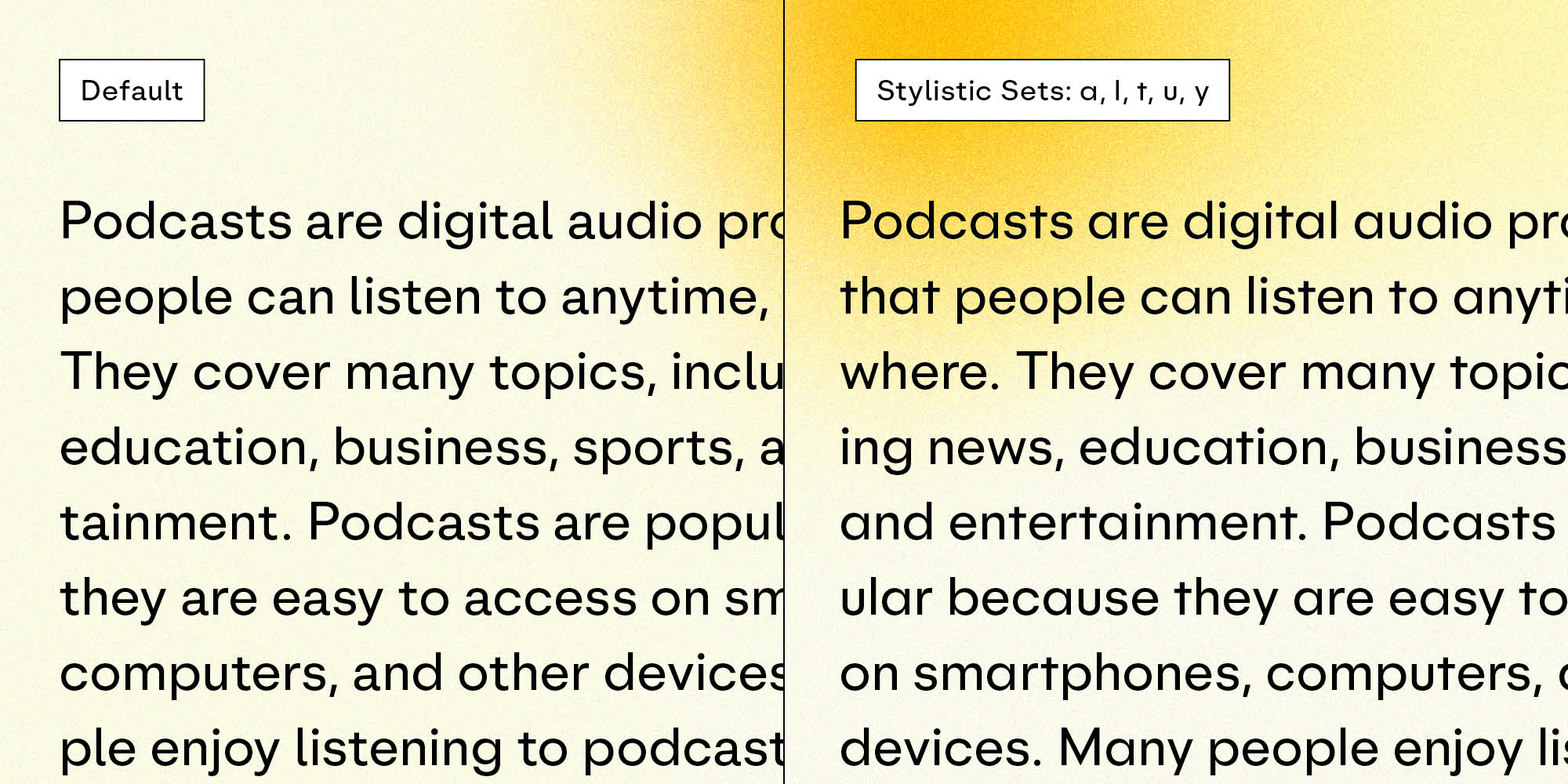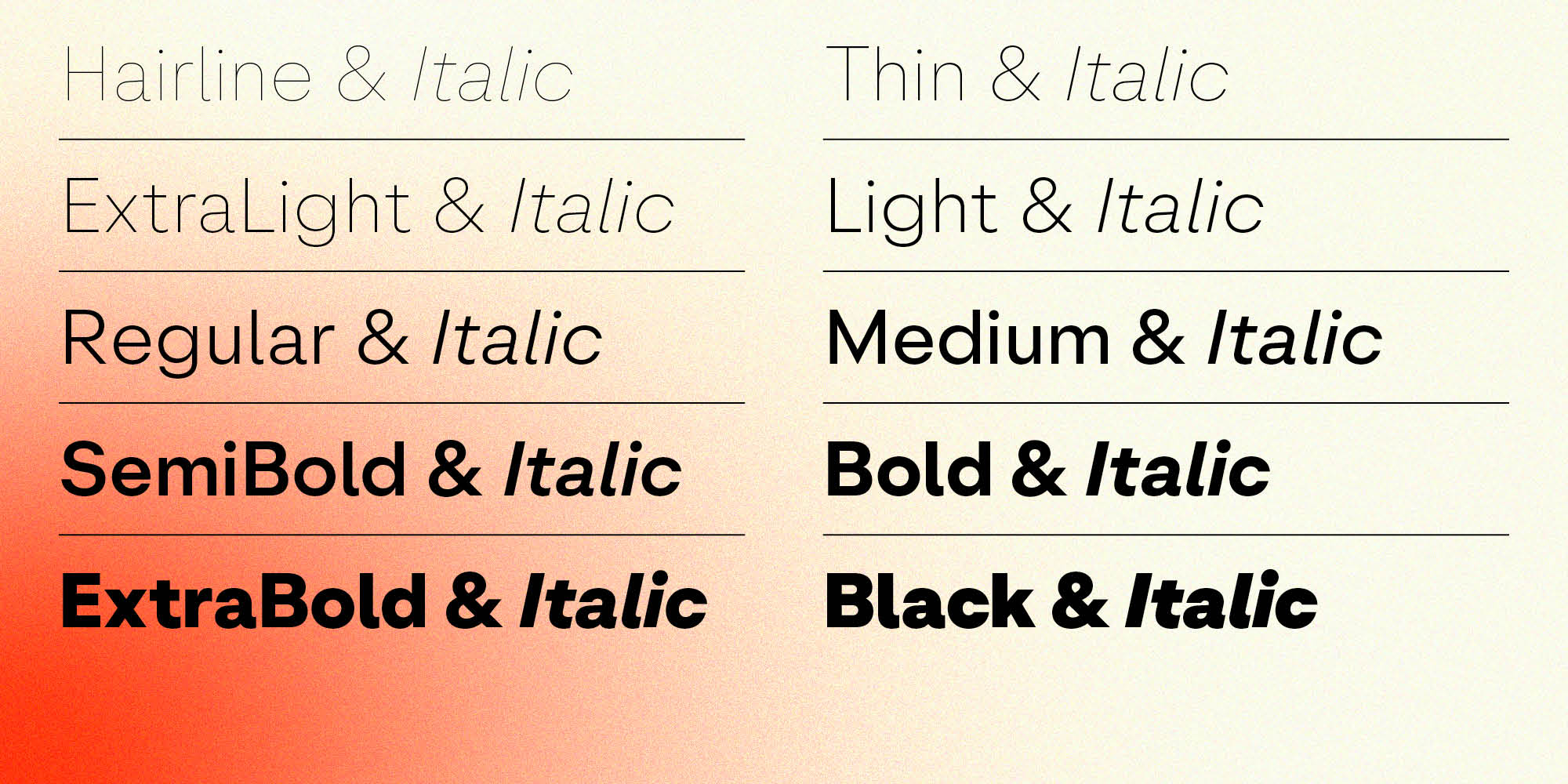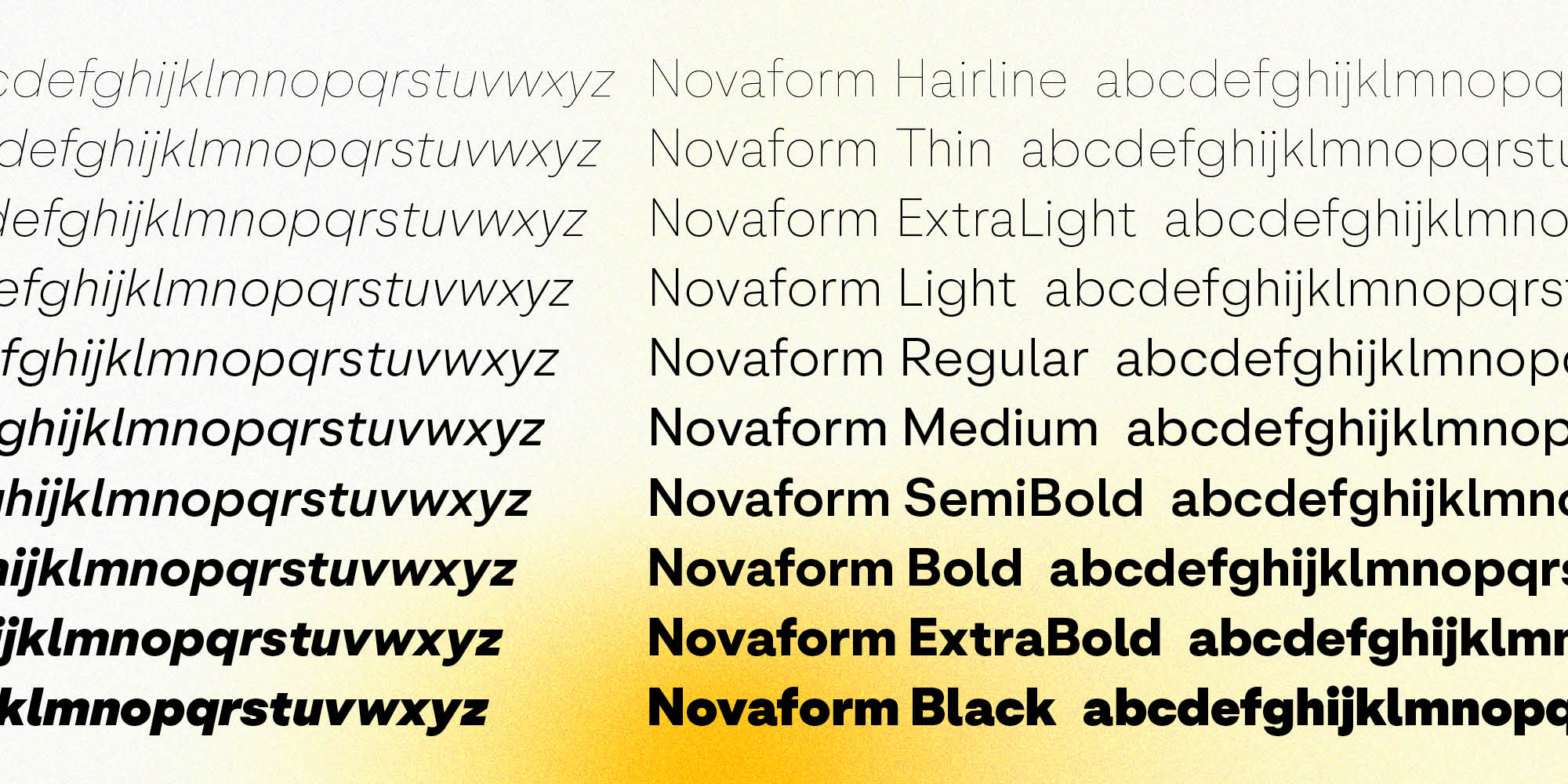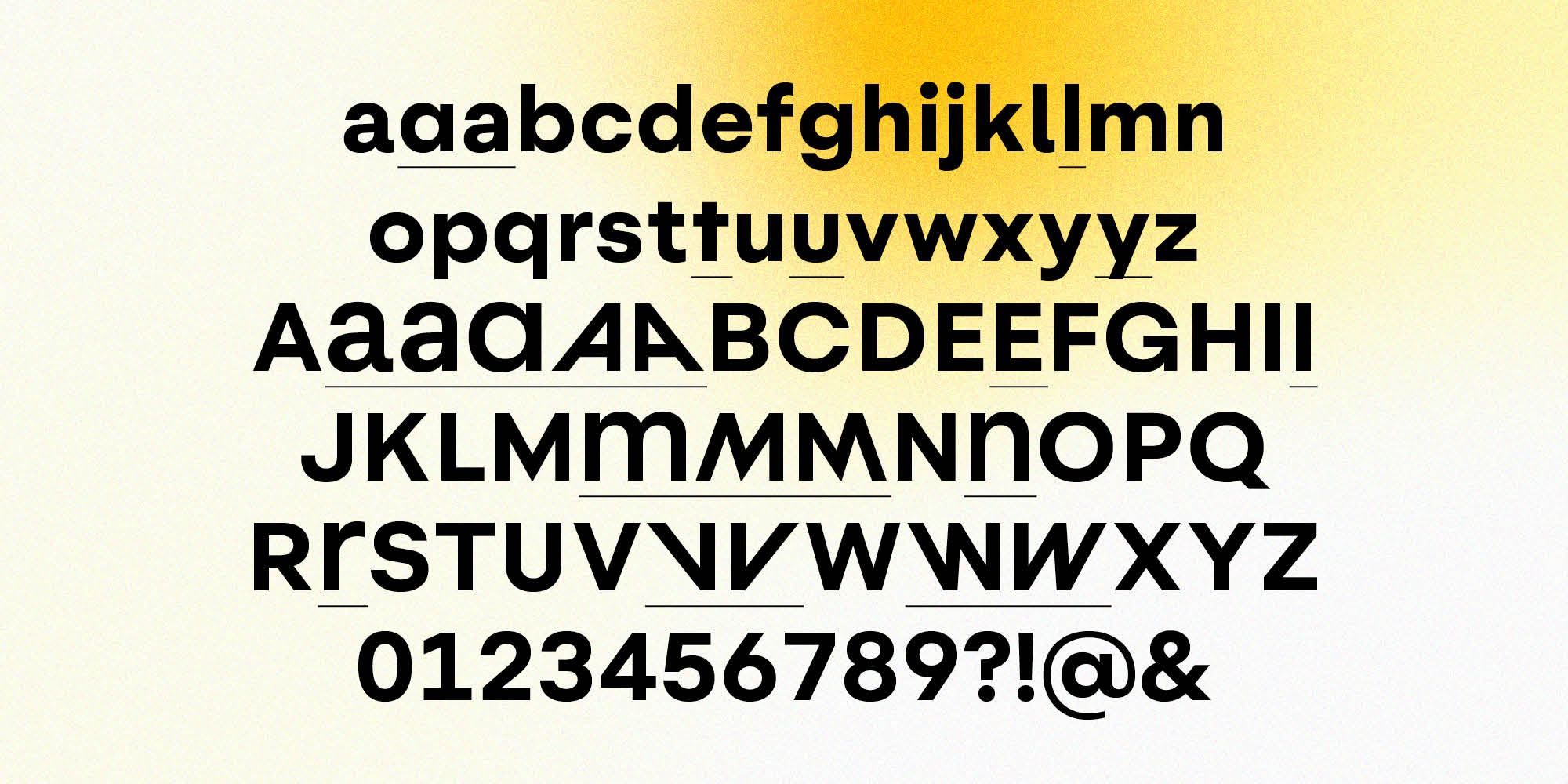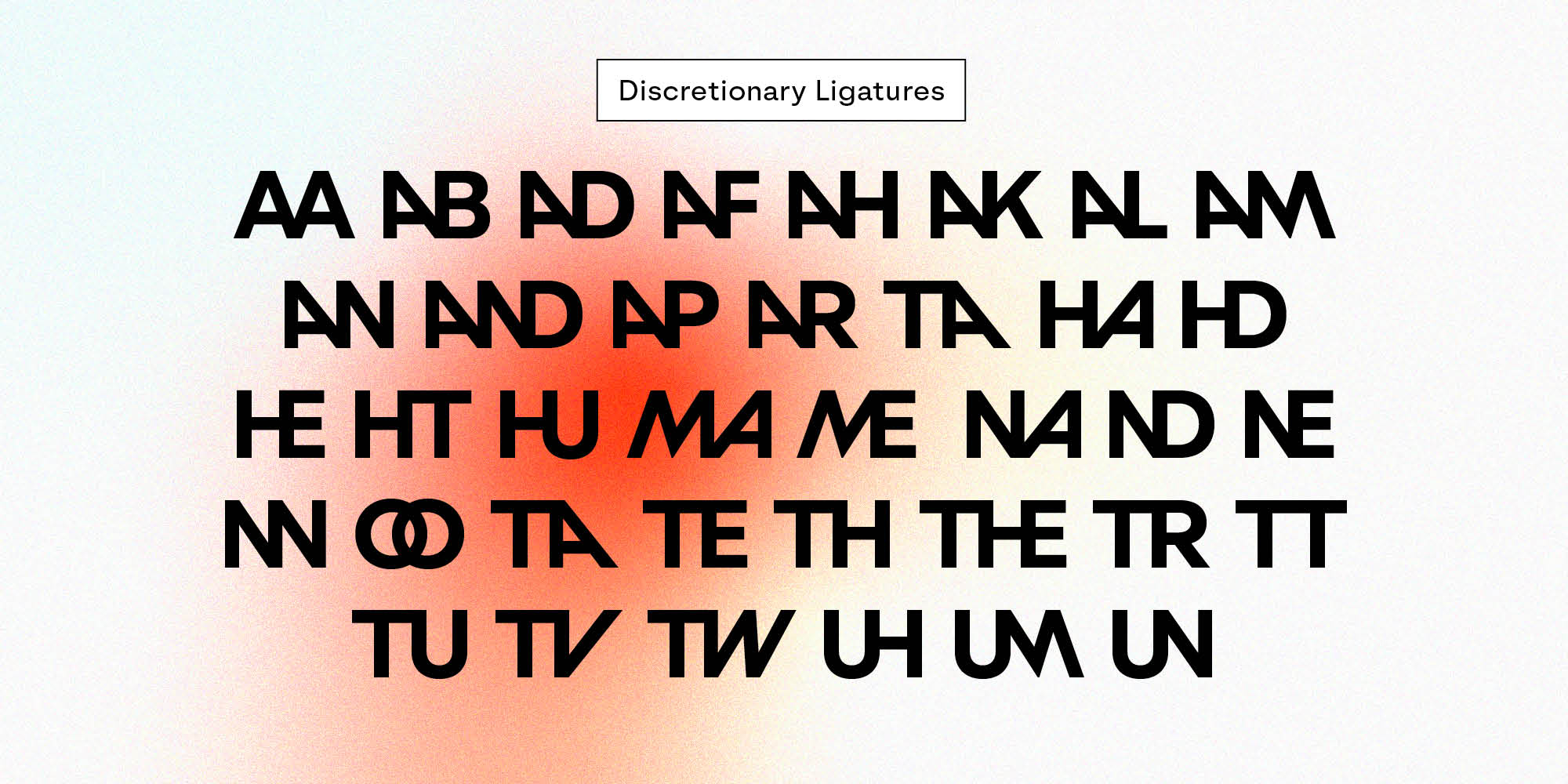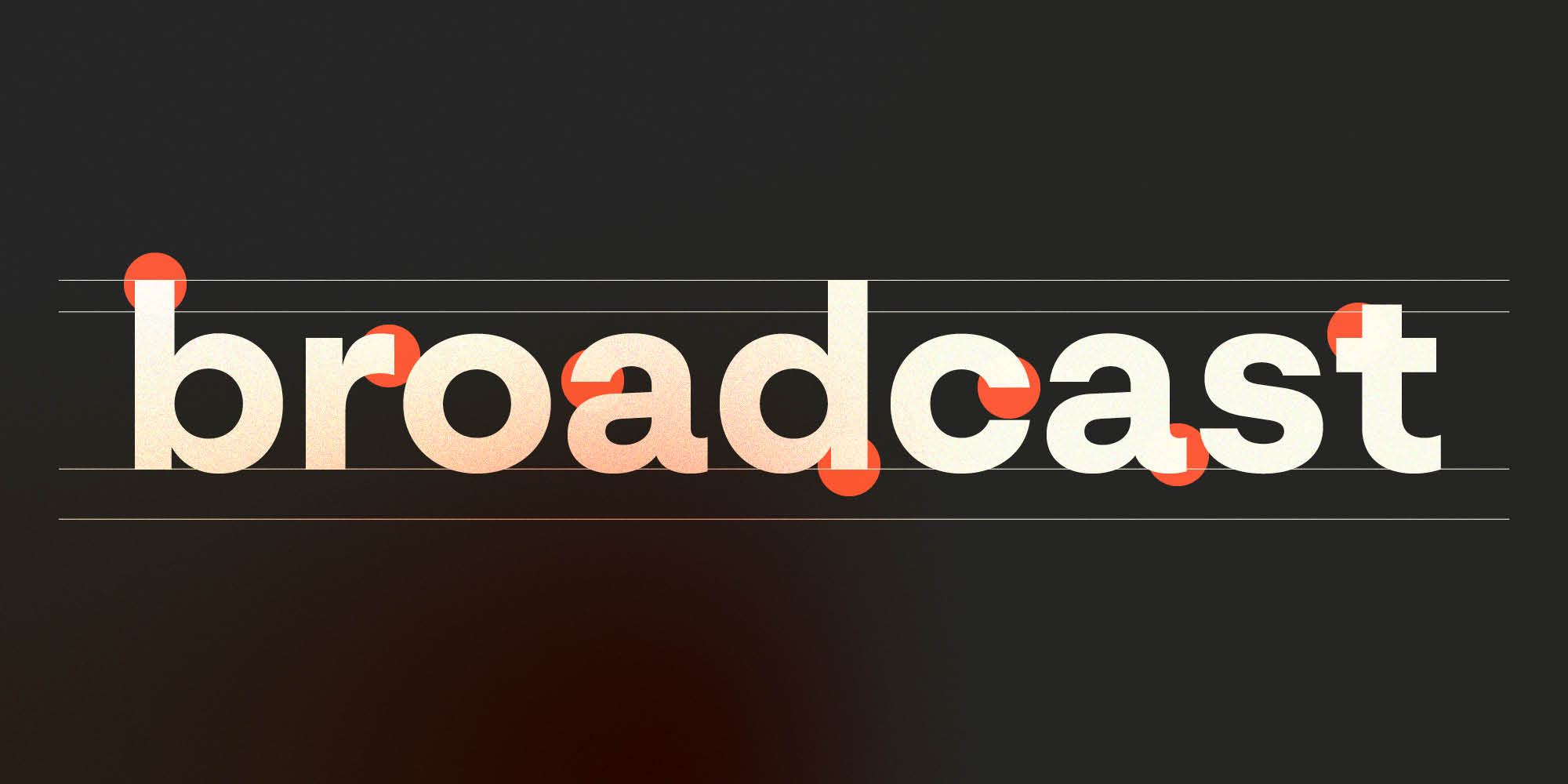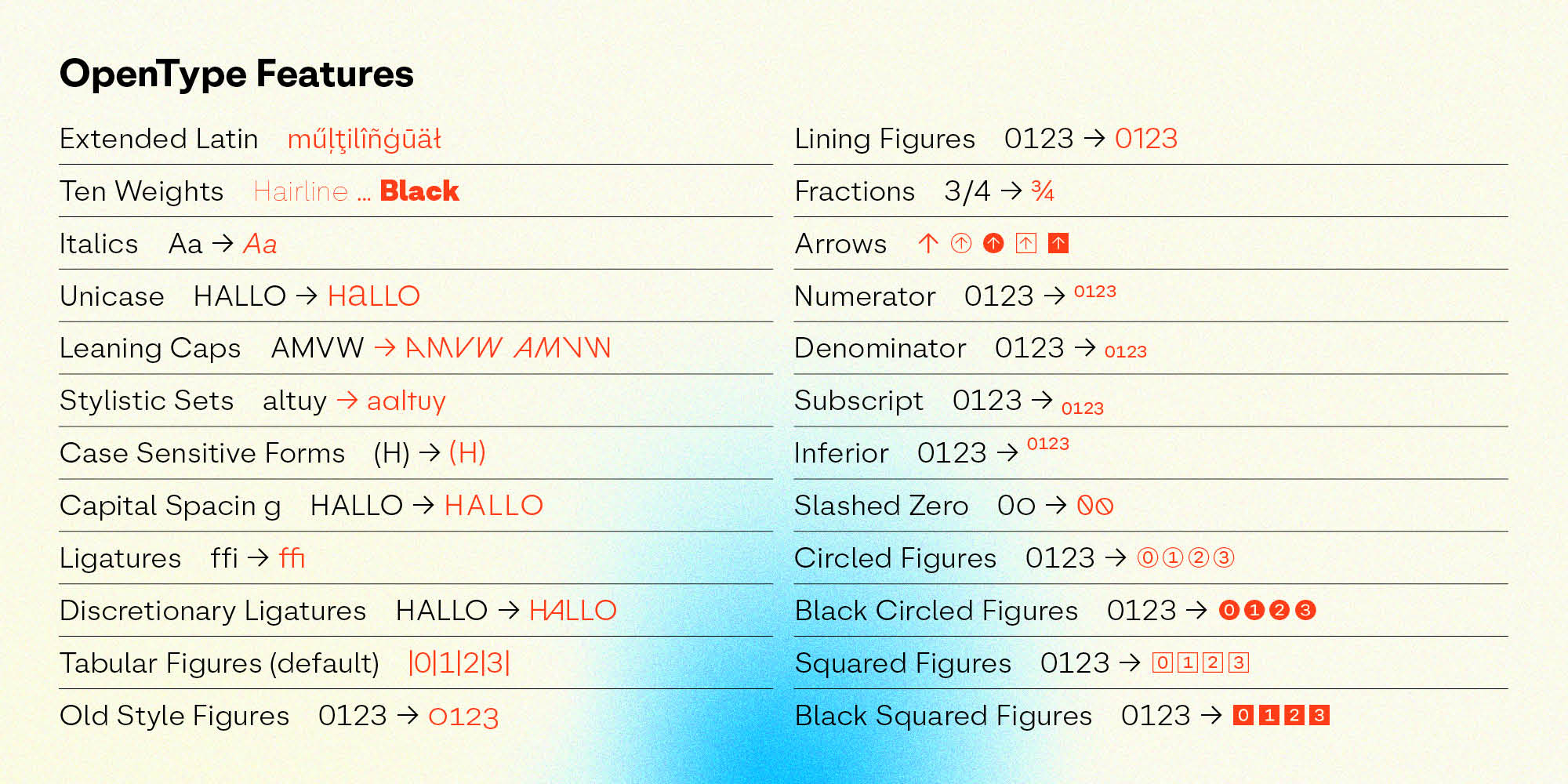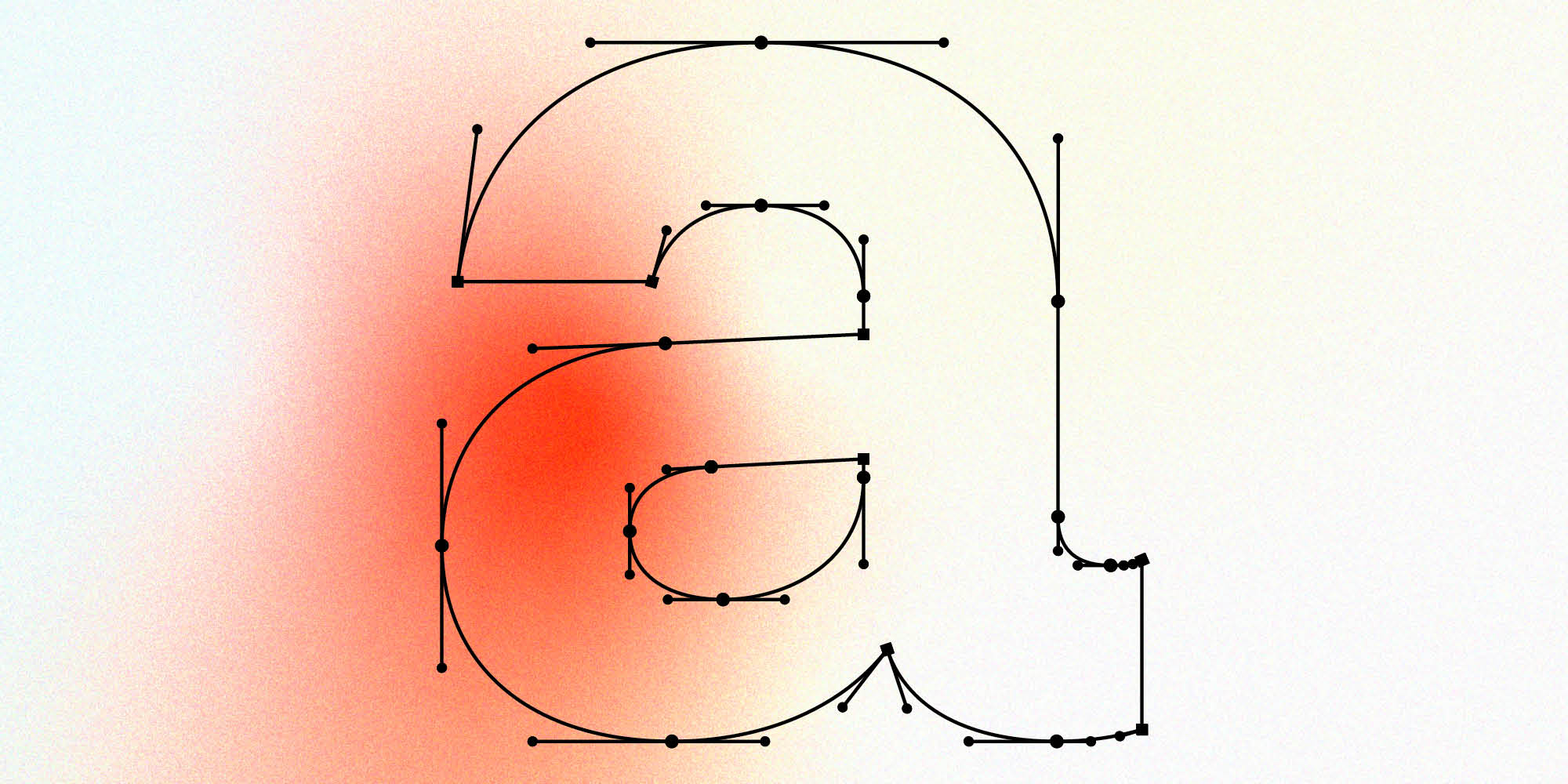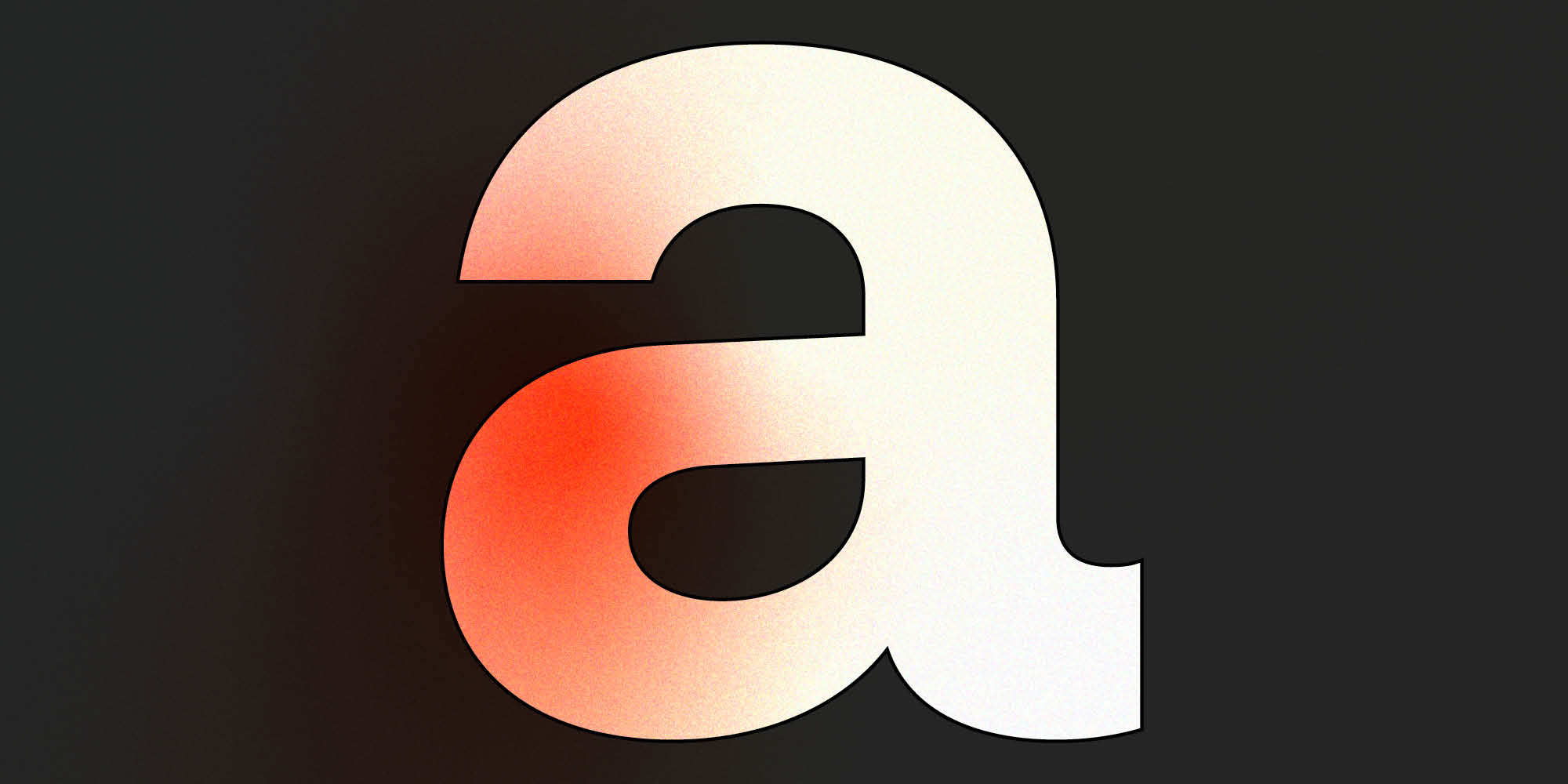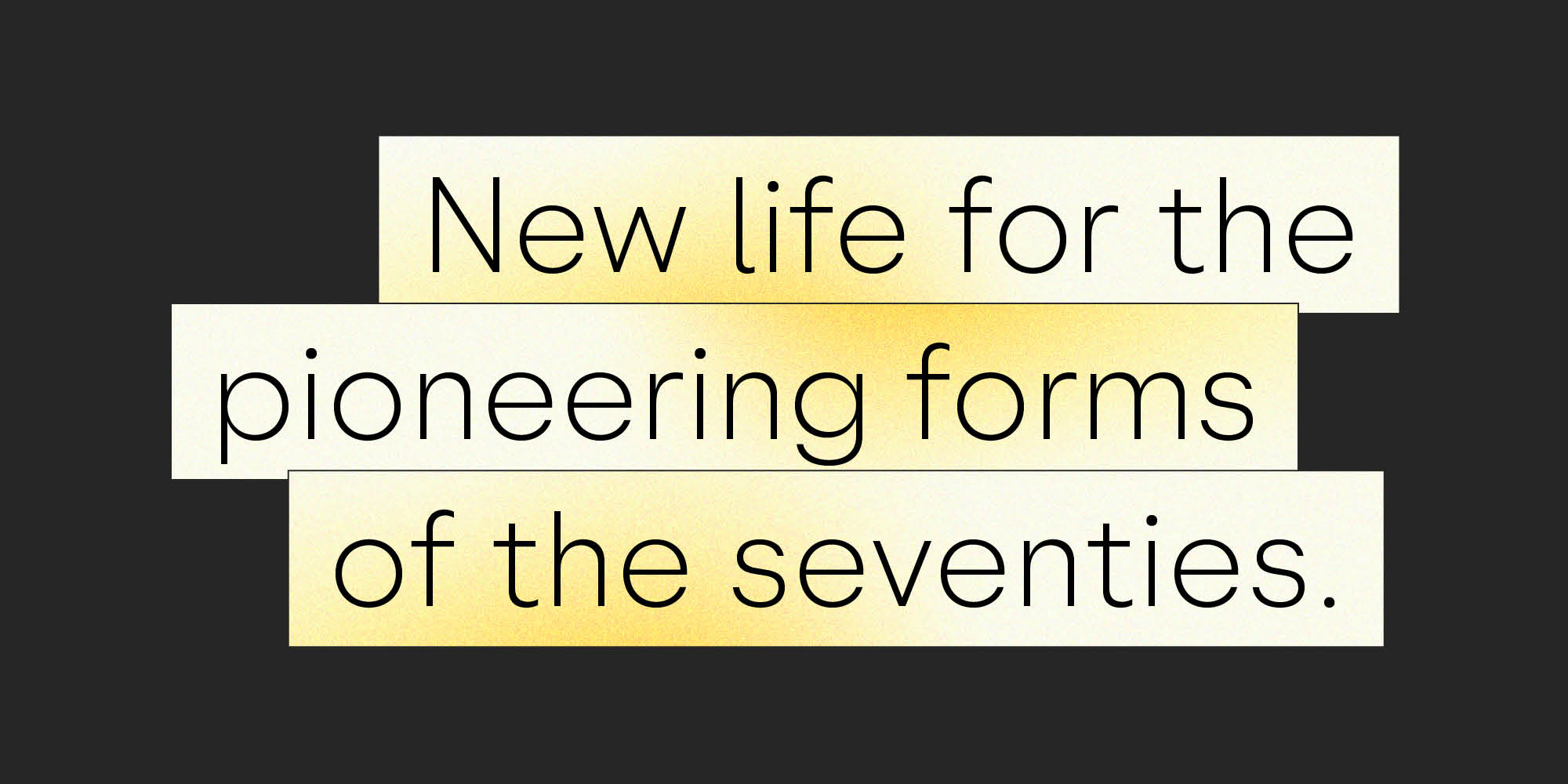
Novaform: Flexibilität statt kompromissloser Geometrie
Die neue Schrift von Identity Letters nimmt Bezug auf Herb Lubalins Erfindungsreichtum und seine Vorreiterrolle in der Schriftgeschichte.
Mutig, innovativ und kompromisslos: So erfüllte Herb Lubalin 1970 den Auftrag, ein Logo für das wegweisende Kunstmagazin »Avant Garde« zu entwerfen. Aus den verschränkten, geometrischen Versalien dieses Logos entwickelte er später eine komplette neue Schriftart für Schaugrößen. Dafür zog er Klassiker des Genres heran, die vor fast einem halben Jahrhundert entwickelt worden waren – zum Beispiel Futura und Kabel – und kleidete sie in ein aufsehenerregendes, Broadway-geeignetes Gestaltungssystem ein. Anders als ihre Vorfahren war die so geborene Schrift für Mengentext weder vorgesehen noch geeignet (was Lubalin durch einen ganzen Satz verschränkter Schmuckligaturen noch unterstrich), dafür aber ideal für Logos und Titel. Paul McNeil nannte seinen Entwurf »die definitive Schrift des Fotosatzzeitalters«. Ein weiteres halbes Jahrhundert später fragten wir uns: Was könnte diese Idee heraus aus dem Fotosatz- und hinein in unser digitales Zeitalter führen?
Wir bei Identity Letters schätzen von jeher Lubalins Erfindungsreichtum und Vorreiterrolle in der Schriftgeschichte. Doch schon in den 1970er Jahren war der richtige Umgang mit einem schaugrößenorientierten Abkömmling von Kabel und Futura zuweilen schwierig. Auch für die Schriftsetzer von heute ist es eine Herausforderung. Trotz ihres Ikonenstatus ist es nach wie vor zu einfach, die Schrift falsch einzusetzen; denn die etwas unglücklich geratenen Minuskeln und das übermäßig rigide Gestaltungssystem vertragen sich nur bedingt mit unbegrenzten Möglichkeiten der Skalierung und Transformation (was auch schon im Fotosatz der Fall war). So haben viele Designer Probleme mit der richtigen Anwendung. Wo etwa ist der Kipppunkt zwischen Schau- und Lesegröße, Titel und Text? Wann geht Identität zulasten der Leserlichkeit? Eine gute Schrift von heute sollte solche Fragen leicht beantworten – oder diese gleich hinfällig werden lassen.
In diesem Sinne ist Novaform unsere zeitgenössische Antwort auf die geometrischen Schriftgestaltungssysteme der 1970er Jahre. Nach wie vor ist der Kreis das definierende Element, wodurch O und o sehr breit und U und n sehr schmal werden – bei insgesamt eher klassischen Proportionen. Kleine Punzen und schmale Öffnungen betonen den grafischen Ursprung des Gestaltungsprinzips. Doch Novaform wurde im Sinne von Flexibilität gestaltet, nicht kompromissloser Geometrie. Typedesigner Moritz Kleinsorge, Gründer von Identity Letters, entschärfte sowohl die extremsten Formen als auch die übertriebene x-Höhe und lenkte einige Buchstabenformen behutsam in Richtung gefälligerer, besser lesbarer Groteskformen. Auf diese Weise behält die Schriftart den stilisierten Charakter ihrer Vorgänger bei und tritt dennoch souverän und leserlich im Fließtext auf. Novaform liest sich natürlicher und strahlt dabei weiterhin den optimistischen Geist der bahnbrechenden Ideen aus, die ihrer Gestaltung zugrundelagen.
Verschränkte Schmuckligaturen waren ein prägendes Merkmal der Fotosatzära. Sie waren so gefragt, dass teilweise sogar die entsprechenden Stempel für den Bleisatz nachgeschnitten wurden. Logisch, dass Novaform dieses schaugrößenorientierte Merkmal aufgreift und eine Palette von mehr als 40 solcher Ligaturen anbietet, die sorgsam für den unmittelbaren Einsatz austariert wurden. Mit einem einzigen Klick lassen sich Logos per Navigation durch die Stilsets aufpeppen. Weitere 40 Alternativen gibt es bei den Versalien. Die Geneigten oder Leaning Caps helfen dabei, eigene Ligaturen für knackige Wortmarken und spannenden Titelsatz zu entwickeln. Und sogar einen dritten Schaugrößenmodus führt Novaform ein: Unicase. Hier wird eine Auswahl von Versalien ersetzt durch ihre neugezeichneten und auf Versalhöhe gebrachten Minuskel-Äquivalente – eine faszinierende Form von Gemischtsatz für typografische Hingucker.
Jeder der 20 Novaform-Schnitte – von Hairline bis Black – wartet mit mehr als 850 Glyphen auf. Darunter befinden sich sieben Ziffernsetzs, Zusatzvarianten für Pfeile und Zahlen (in Kästen und Kreisen, positiv und negativ), Stilalternativen für Minuskeln und Versalien (etwa das zweistöckige a und das schlichte t) und lokalisierte Varianten sowie solche für den Versalsatz.
Gäbe es das Magazin »Avant Garde« auch heute noch, würden wir ein Redesign mit Novaform feiern. Doch die geometrische Schriftfamilie ist zu vielseitig, um sie auf Kunstzeitschriften zu beschränken. Dank ihrer Flexibilität und ihrer OpenType-Funktionen eignet sie sich für vielfältige Anwendungen – von Packaging über Editorial bis zu Identities. Und das quer durch alle Branchen: sie passt zu Gesundheit, IT, Bildung, Recht, Technologie, Kommunikation, Dienstleistungen, Logistik, Unterhaltung, Lebensmittel, Getränke und Mode. Wie auffällig sie dabei auftritt, kann der Anwender bis ins Detail steuern.
Moritz Kleinsorge und sein Team hoffen, Kreative auf der ganzen Welt machen sich die Möglichkeiten von Novaform zu eigen und bereichern unsere visuelle Kultur mit den neuen Formen, die ihrer eigenen Fantasie entspringen.